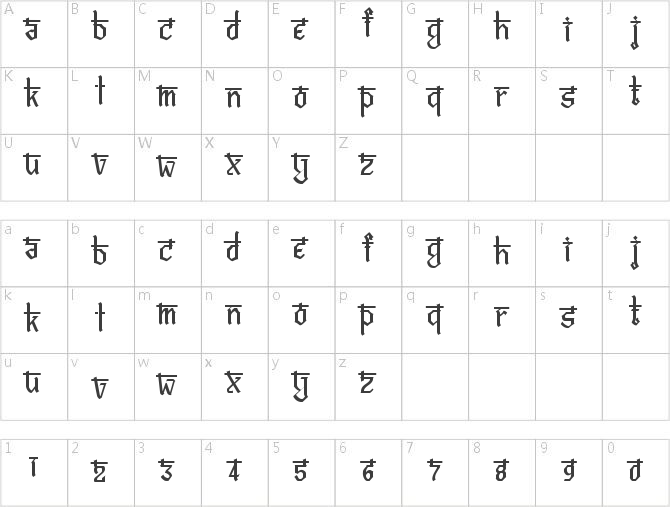
字體名稱: Bitling
Bitlingvedas-Regular
Bitlingvedas-Regular介紹
Bitlingvedas-Regular字體字庫是一款讓人賞心悅目、百看不厭的英文字體,適合各類廣告和產(chǎn)品包裝設計應用,字體大小0.04MB,格式為ttf字體,上傳用戶是星期一,作者/版權方為未知